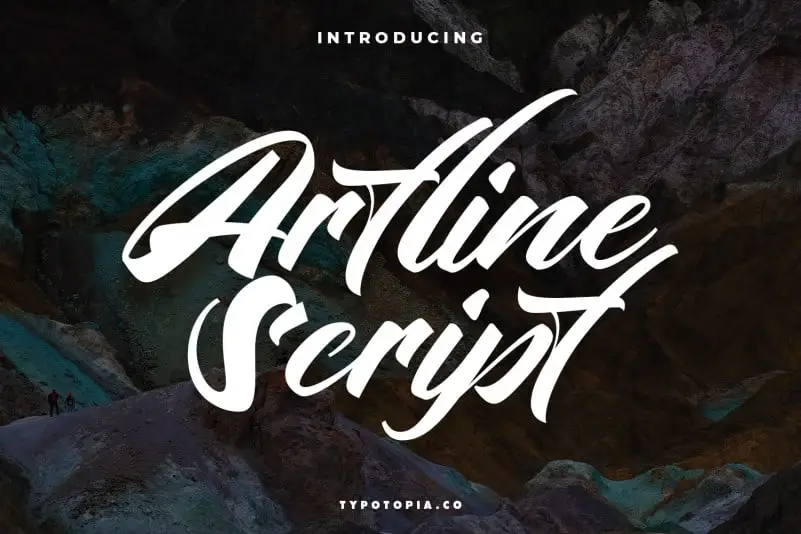
Artline Fancy Script Font – Download Grátis
Introduzimos a Artline Script Font, uma família de fontes tipográfica que se destaca pela sua elegância e personalidade única. Esta fonte foi projetada especialmente para uso em diversas aplicações gráficas, incluindo logomarcas, panfletos, material de escritório, revistas, menus, livros, convites, cartões de agradecimento, embalagens, etiquetas, roupas de moda e materiais de marketing. A Artline Script Font é uma escolha perfeita para quem busca um toque sofisticado em sua tipografia, seja para criar o próximo logo da sua marca ou para tornar os seus materiais gráficos mais atraentes e diferenciados. Com uma aparência fluida e detalhada, essa fonte oferece uma ampla gama de opções de personalização que certamente atenderá às suas necessidades em design criativo. Descubra por si mesmo como esta belíssima família de fontes pode enriquecer seus projetos.